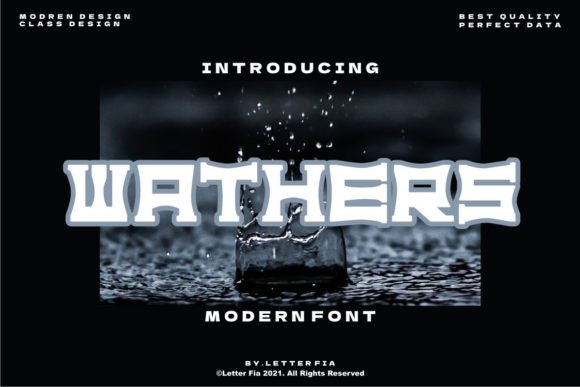
Creativefabrica Wathers Font 2021
[Creativefabrica] Wathers Font (2021)
Wathers - это крутой, современный и смелый шрифт.
Этот шрифт идеально подходит для написания веб-дизайнов, визитных карточек и практически всего остального, что требует уникального штриха.